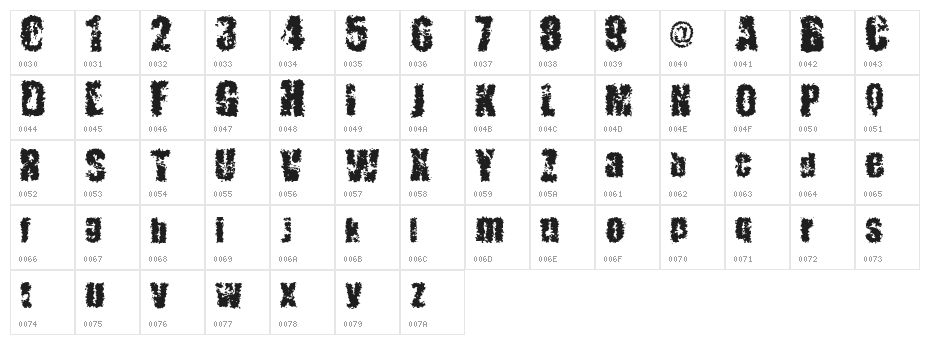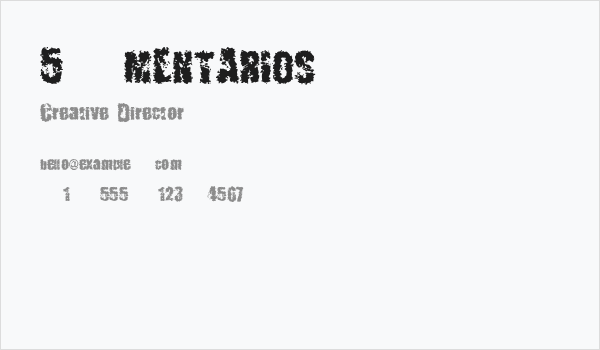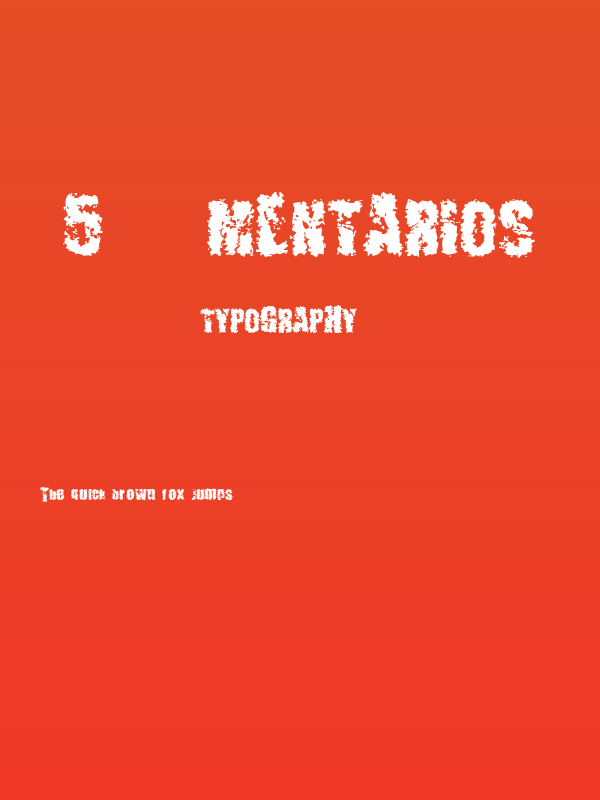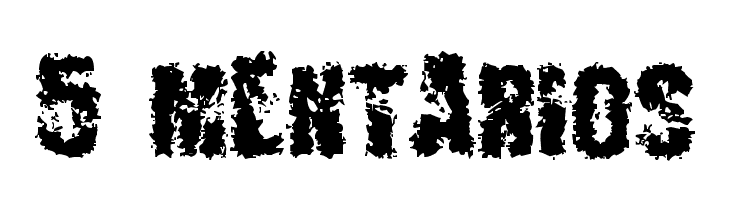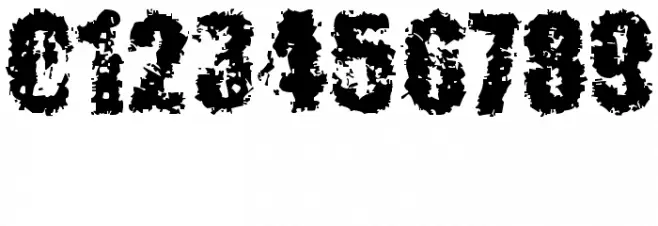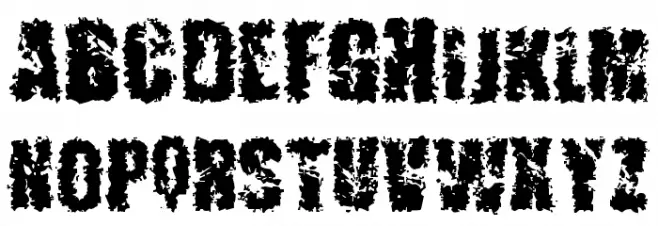
5+MENTARIOS Font
| Vorgeschlagene Projekte | Ideal for album covers, posters, branding for extreme sports, or any project needing a gritty, impactful look. |